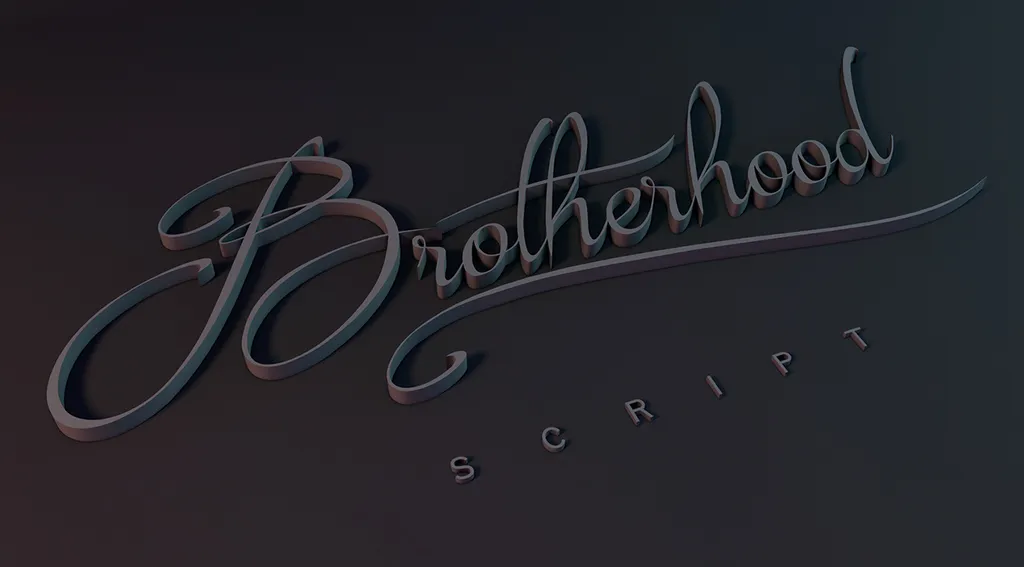
A fonte “Brotherhood Script” é uma escolha perfeita para quem busca adicionar um toque elegante e sofisticado a seus trabalhos digitais. Desenvolvida pelo designer Hamilton, esta fonte script abraça a natureza variada do idioma português com grande suavidade e graça. Para os criadores de materiais pessoais e hobbies, como blogueiros, designers gráficos ou artistas independentes que desejam incorporar um charme único em seus projetos digitais, “Brotherhood Script” oferece uma versão gratuita. Mas para as necessidades mais avançadas, incluindo aplicativos comerciais e produtos pagos, é sempre necessário entrar em contato diretamente com o designer. Esta fonte traz a você um conjunto refinado de letras que flutua e se movimenta de maneira encantadora, proporcionando aos seus projetos um toque único e sofisticado. Com “Brotherhood Script”, transforme seu design em algo ainda mais especial e memorável.